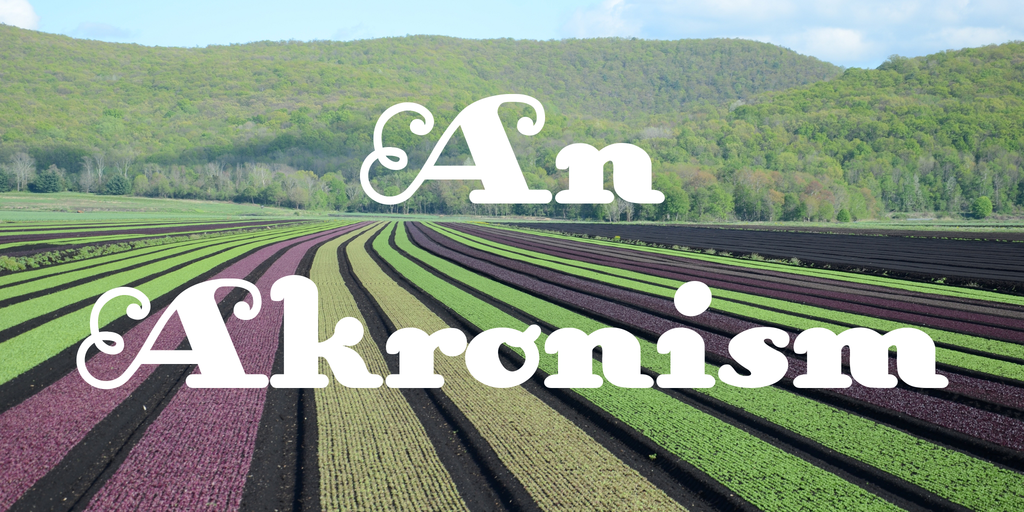
An Akronism Font é uma elegante escolha para designers buscando algo único e intrigante. Inspirada no estilo Blackletter, essa fonte oferece uma paleta vibrante de desenhos esculpidos com um toque distintivo e arcaico. Hamilton, o designer, conseguiu criar linhas que são tanto atemporais quanto contemporâneas, combinando elementos manuscritos com linhas robustas para criar um conjunto de caracteres atraente e versátil. Ideal para uso em designs históricos, clássicos ou até mesmo em design gráfico retro, essa fonte é perfeita para aqueles que valorizam uma dose única de personalidade no seu trabalho. Sua natureza única faz do An Akronism Font uma opção incrível para qualquer designer em busca de algo novo e interessante.